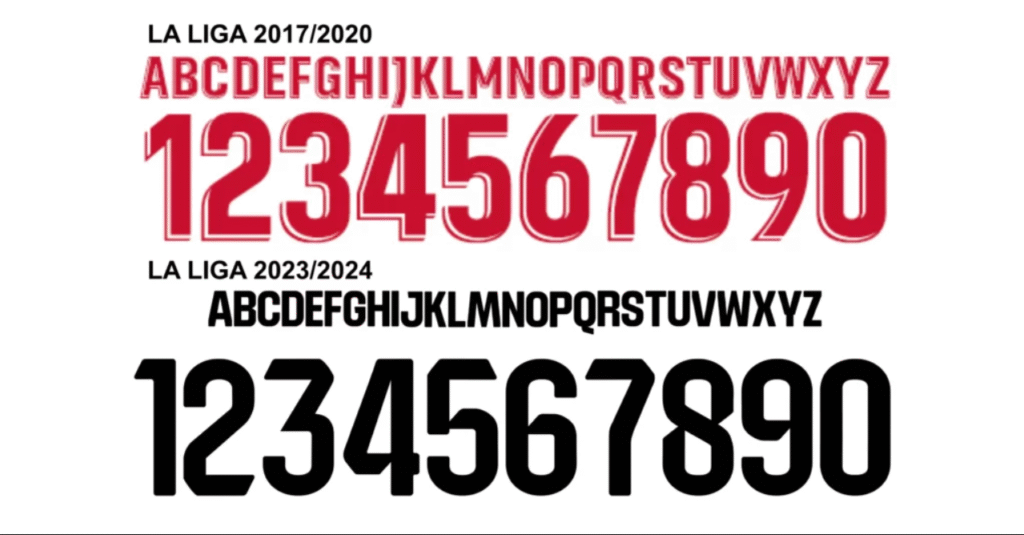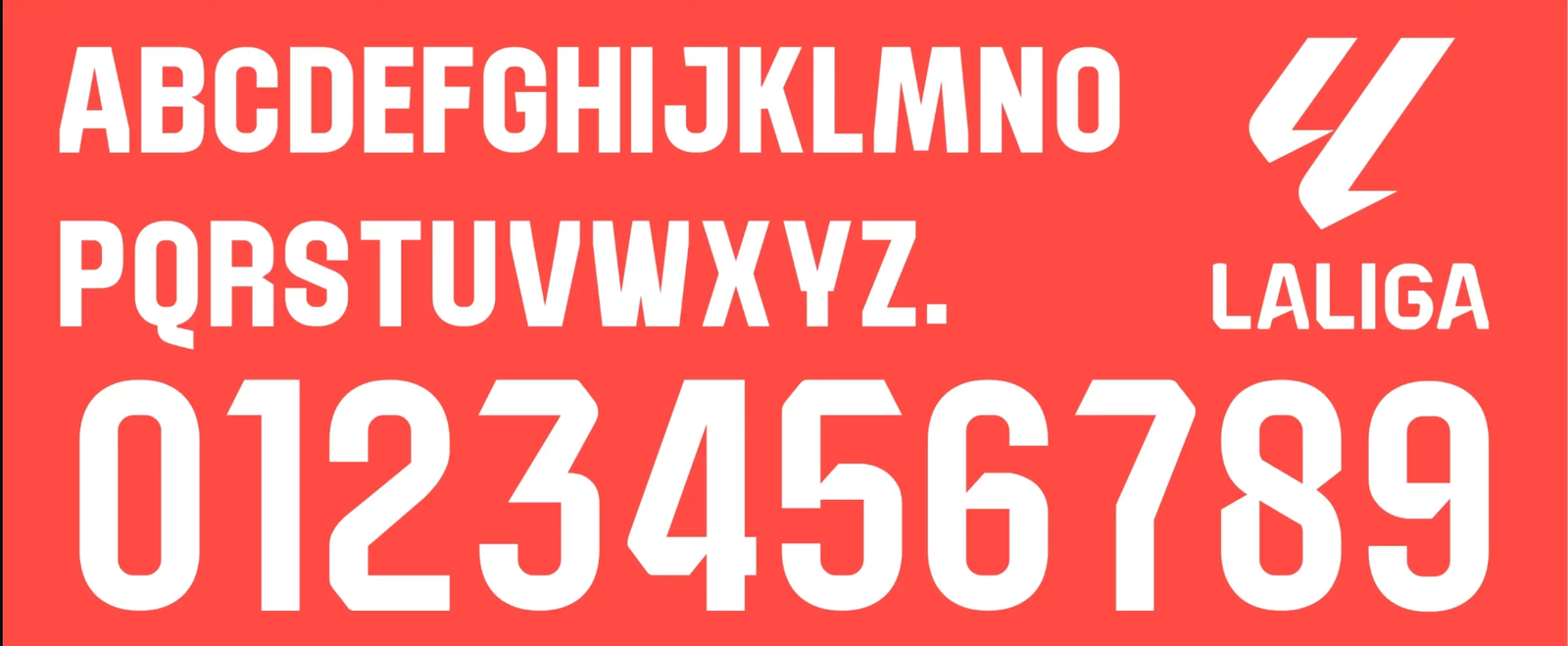
A temporada 2023/2024 marcou uma revolução na identidade visual do futebol espanhol. Com a transição para LaLiga EA Sports, não foi apenas o logotipo da competição que mudou: a tipografia dos uniformes também foi totalmente redesenhada para refletir uma era mais moderna, digital e dinâmica.
Neste post, você tem acesso à fonte padronizada utilizada por quase todos os clubes da elite espanhola, incluindo gigantes como FC Barcelona, Atlético de Madrid, Sevilla e Real Betis durante as partidas da liga nacional.
Estilo Visual e Aplicação
A nova fonte de LaLiga rompe com o estilo arredondado e condensado das temporadas anteriores. A tipografia atual aposta em um visual mais “blocky” (blocado) e geométrico, projetado para maximizar a legibilidade tanto nas transmissões 4K quanto nos dispositivos móveis.
Ela transmite solidez e energia. Vale lembrar que esta é a fonte obrigatória para os jogos do campeonato espanhol. Mesmo times patrocinados pela Nike, Adidas ou Puma devem aplicar esta tipografia específica nas rodadas nacionais, o que a torna um arquivo indispensável para o seu acervo de personalização.
Dica de Especialista: Se você estiver replicando a camisa do Real Madrid, atente-se: o clube merengue costuma vender a camisa com uma fonte própria (customizada pela Adidas) na loja oficial, mas em campo, durante os jogos de LaLiga, eles utilizam esta fonte padronizada que disponibilizamos aqui.